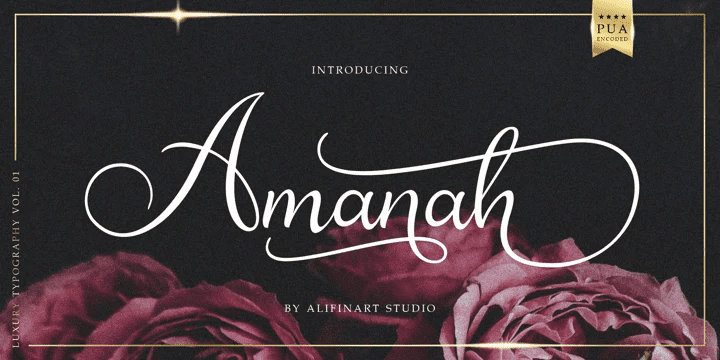
[Myfonts] Amanah Font (2021)
Amanah Script - это рукописный шрифт с непринужденным и современным каллиграфическим стилем. Этот шрифт предлагает большое количество стилистических альтернатив, а также начальные и конечные штрихи.
Всего в шрифте 1660 глифов, включая заглавные и строчные буквы, цифры и знаки препинания, многоязычные акценты, штрихи, а также большое количество стилистических альтернатив и сердечных штрихов (для строчных букв).
Amanah Script можно использовать для оформления свадебных открыток, приглашений, лучше всего подходит для фотографов, путешественников, водяных знаков для блогов и ремесел.